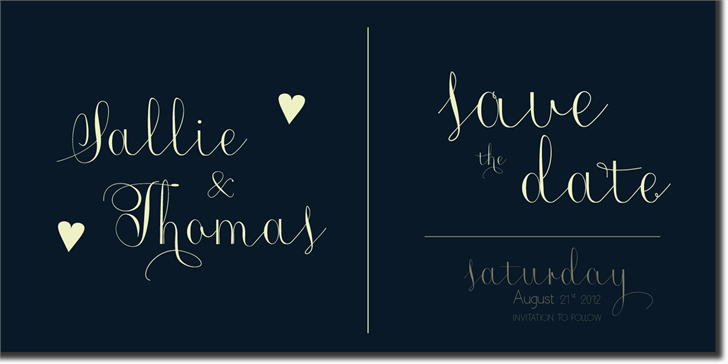
Roicamonta Words font – Fonte Grátis
Roicamonta Words font
A Roicamonta Words é uma elegante e delicada fonte criada pelo designer Hamilton em 2014. Suas linhas femininas e suaves são perfeitas para criar textos agradáveis para cartões de convite, cartas de cumprimento e outros tipos de impressão onde um texto delicado e elegante é necessário. Esta fonte é ideal para quem busca uma gravação suave e sofisticada para seus projetos de design, desde cartelas até obras de arte digitais. Visite a galeria Myfonts (http://myfonts.us/VBRyhn), o Etsy (https://www.etsy.com/listing/183971759/roicamonta-font?cat=2) ou Fontspring (http://www.fontspring.com/fonts/aga-silva-fonts/roicamonta) para adquirir a fonte usada para criar esses textos.